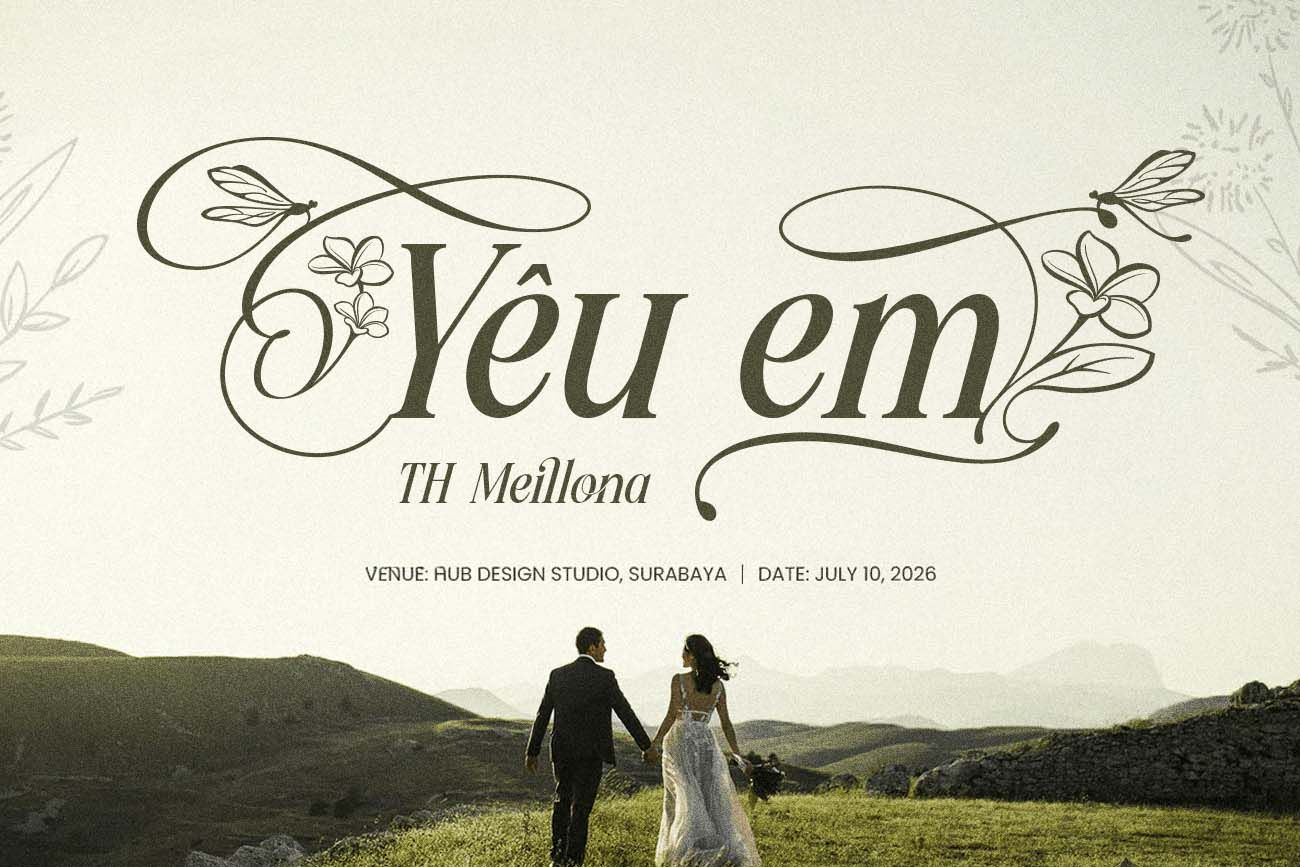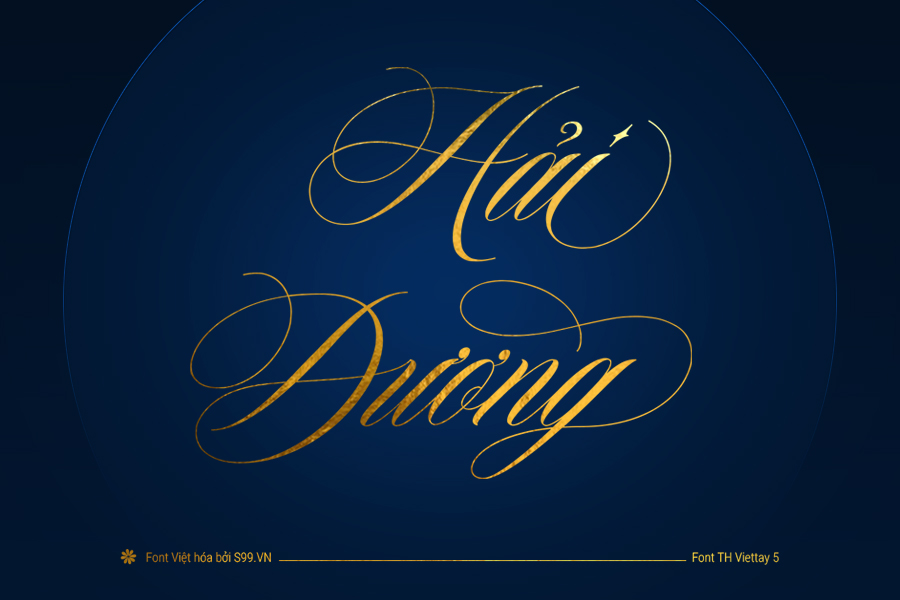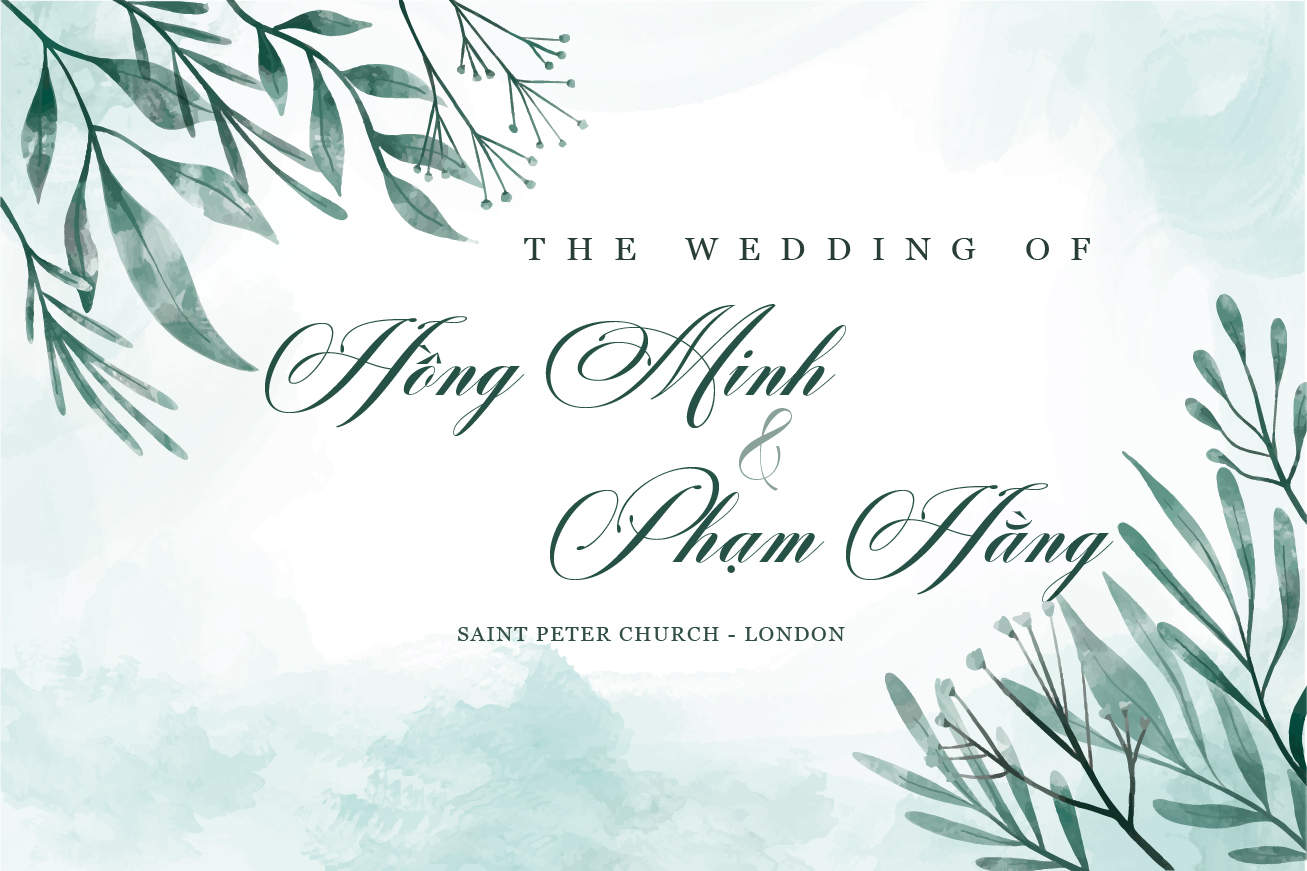
Bộ sưu tập 15 font mềm mại Việt hóa đẹp nhất 2025 từ Fontdep.vn sẽ mang đến cho bạn nguồn cảm hứng mới để biến ý tưởng thành những tác phẩm đầy cảm xúc – từ thiệp cưới, poster, typography đến thương hiệu cá nhân.